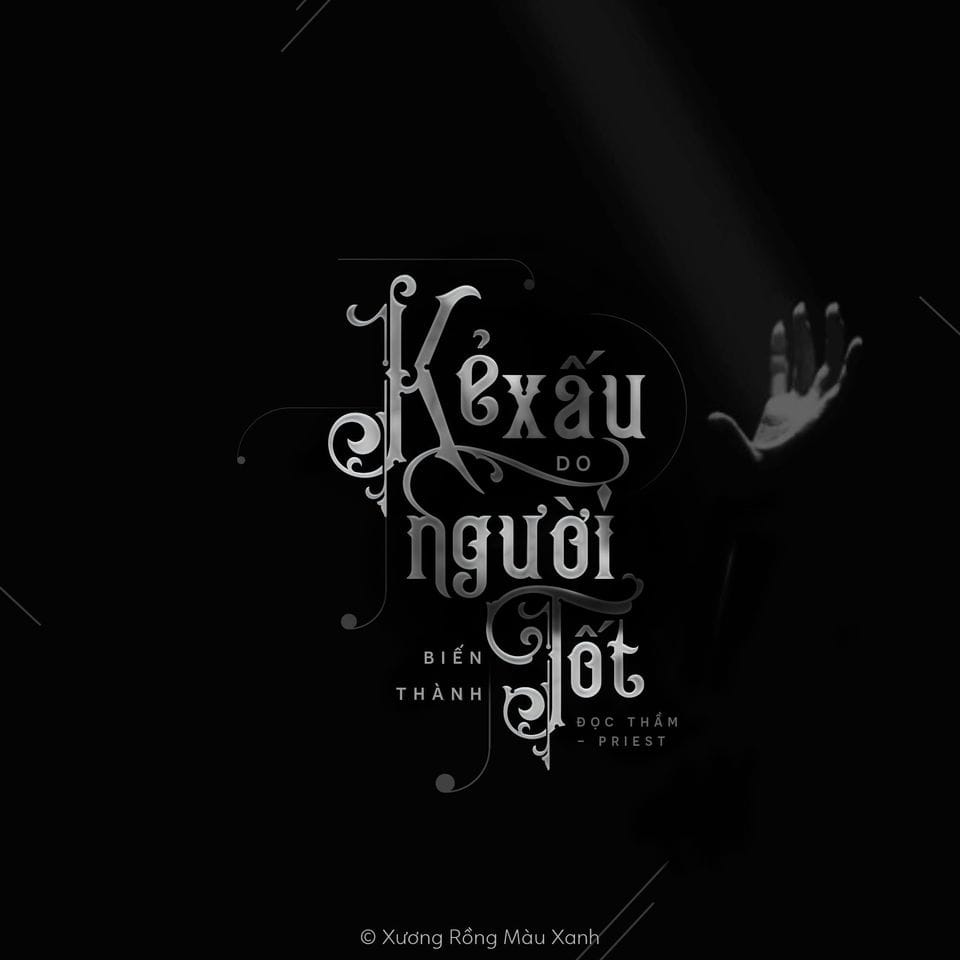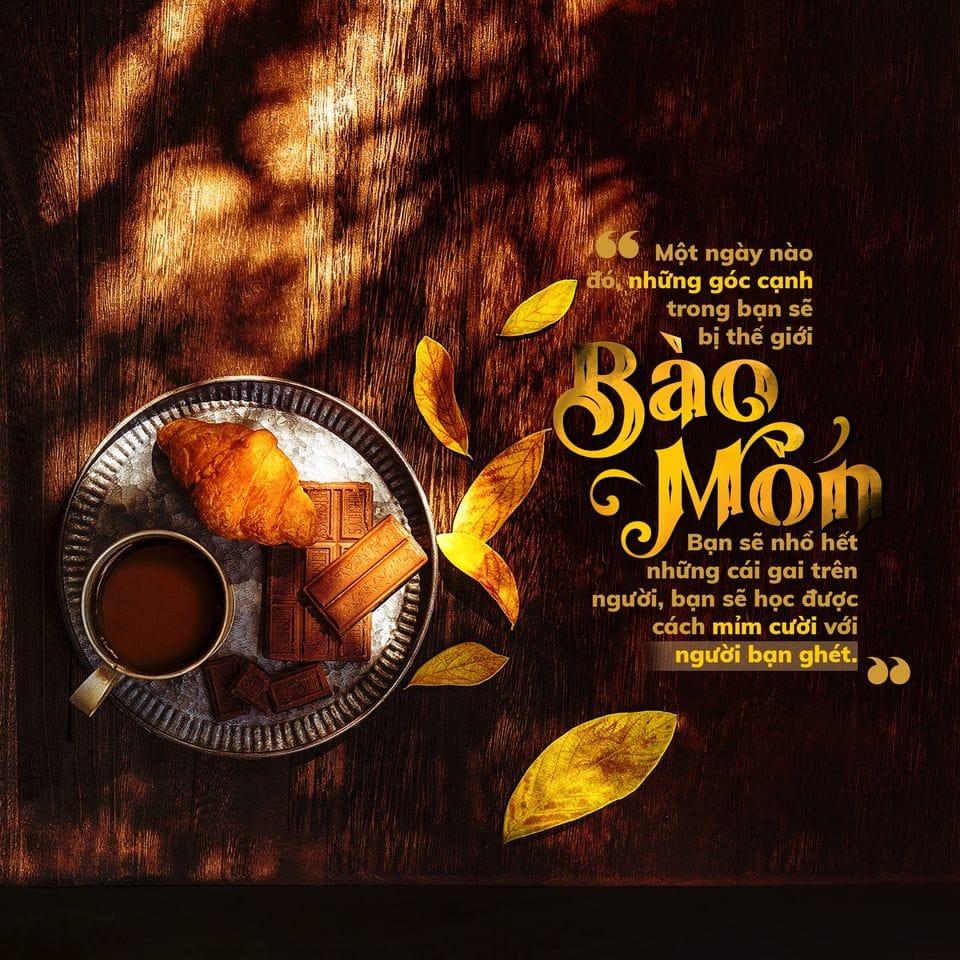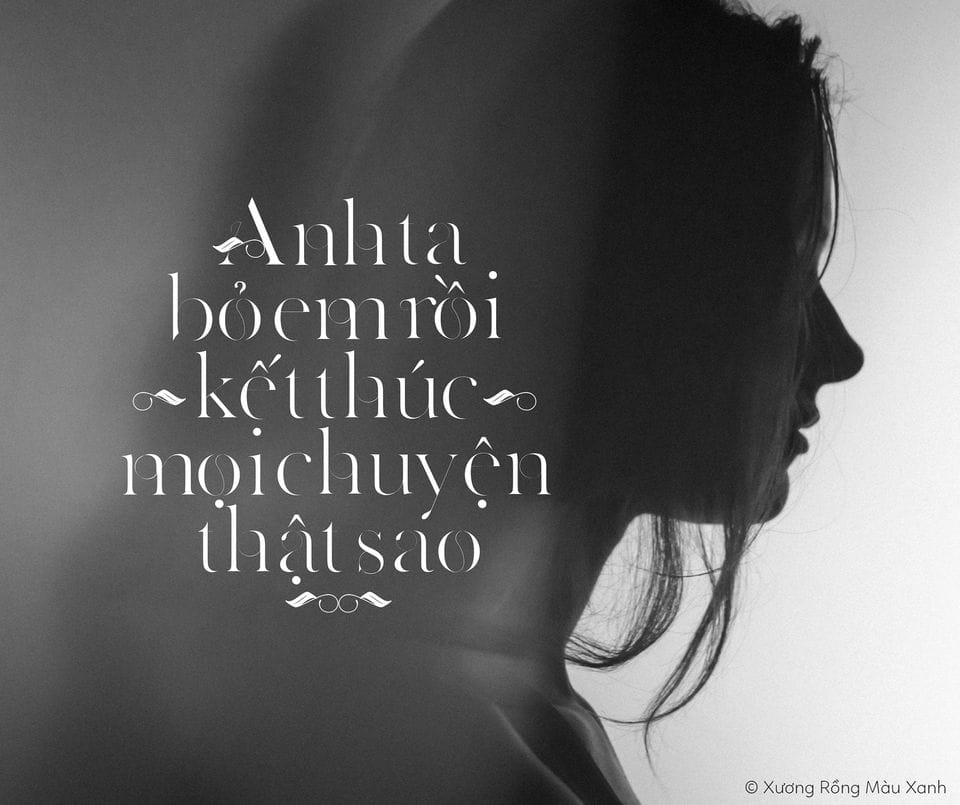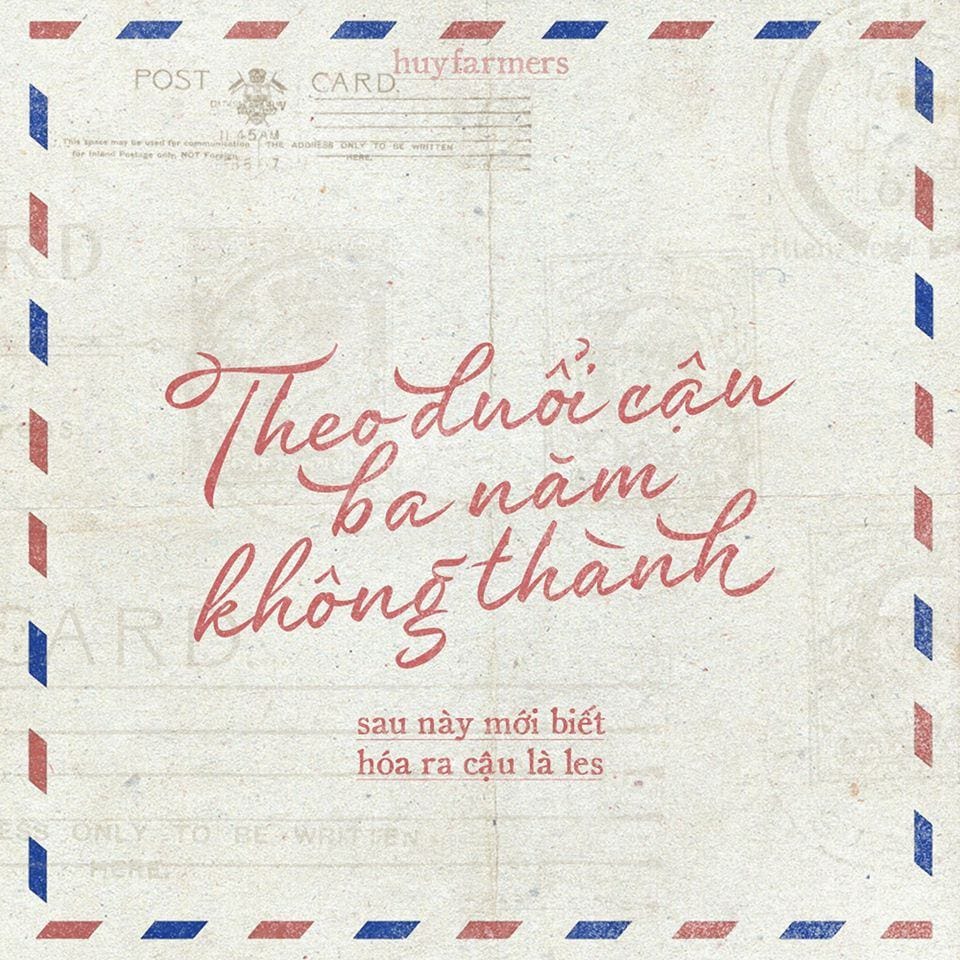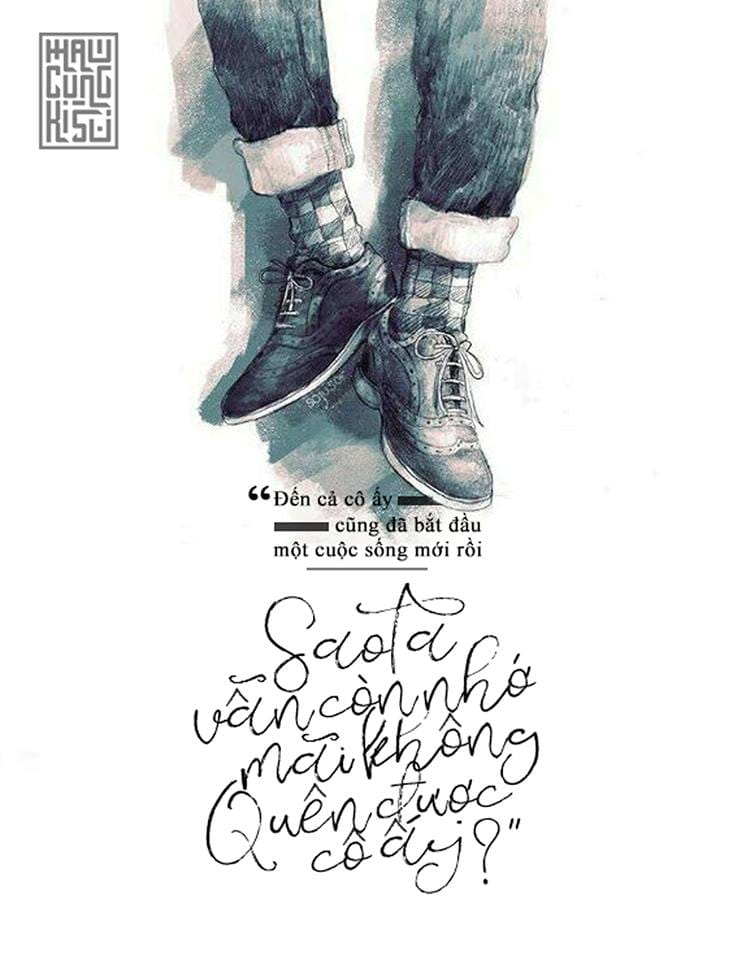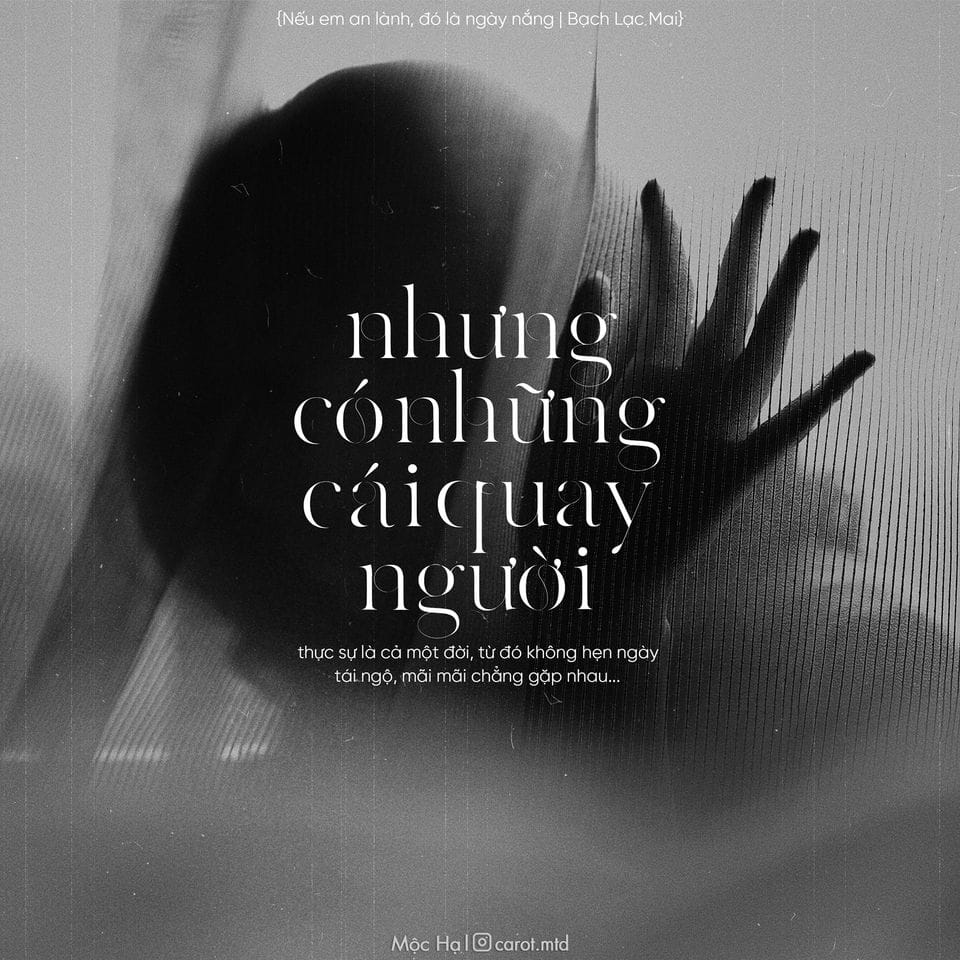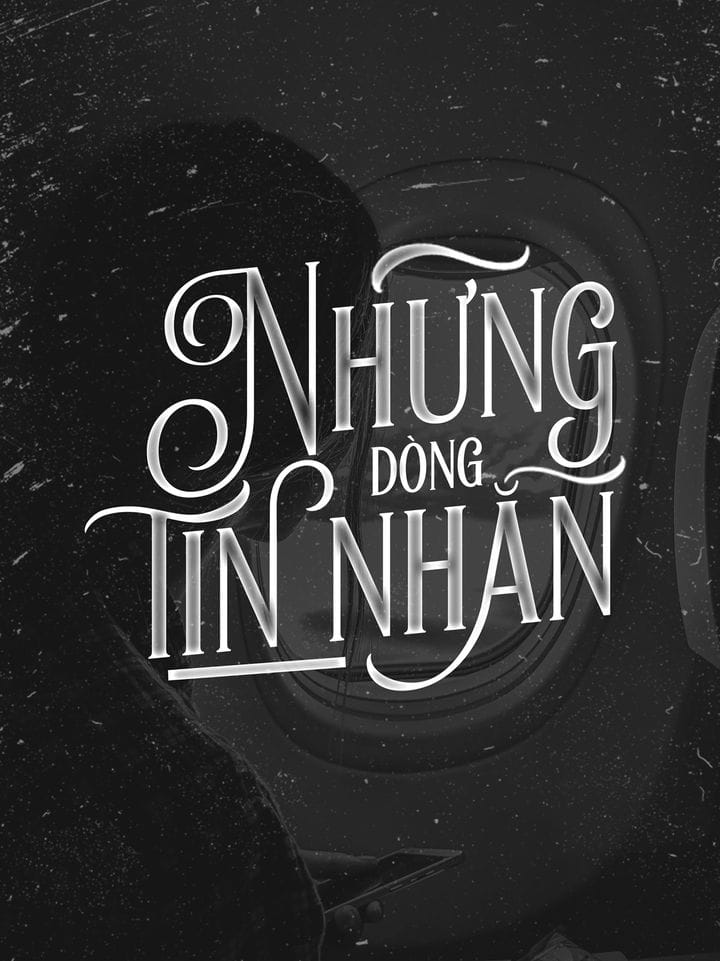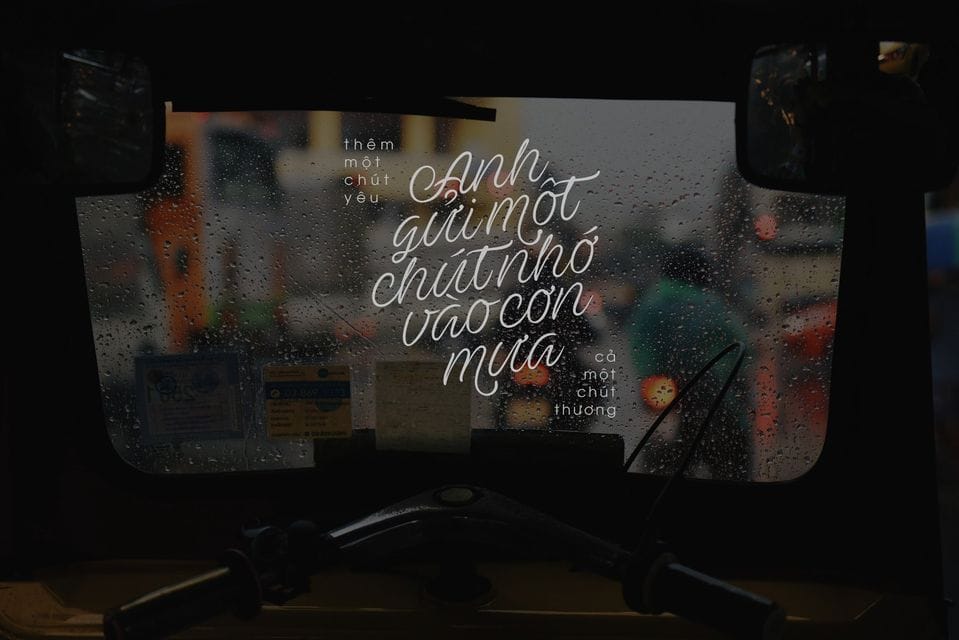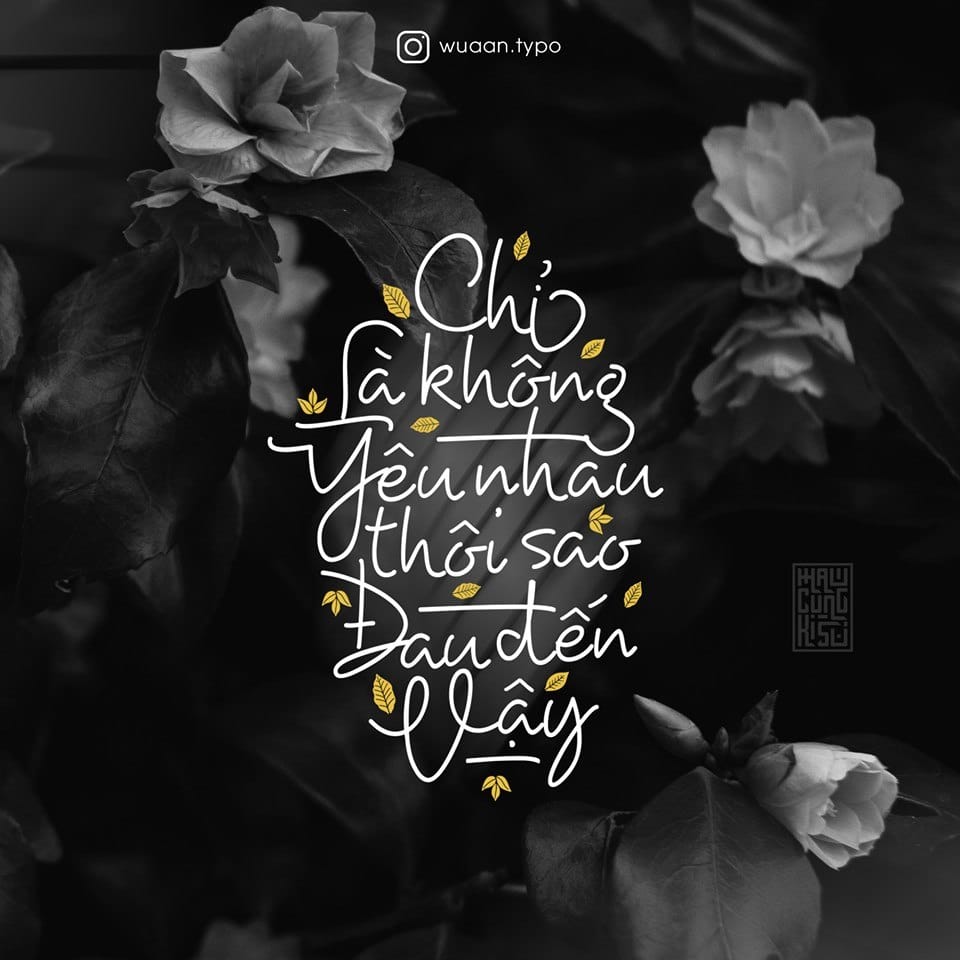
Đây là phần 3 bao gồm 70 font của
bộ font MTD Việt Hóa cực đẹp, có chứa rất nhiều font chữ Script Việt hóa với nhiều phong cách khác nhau rất phù hợp để làm typography cho các video âm nhạc Youtube, banner quảng cáo và nhiều loại hình thiết kế khác.
Việt Hóa bởi Mộc Hạ
Demo một số hình ảnh sử dụng bộ font này:
- MTD 21 Cent
- MTD Antro Vectra
- MTD Arthington
- MTD Artisan
- MTD Ave Utan
- MTD Barakah Regular
- MTD Berrigela Anitta
- MTD Black Baron Gothic
- MTD Blaze Glory
- MTD Britania Letter
- MTD Butter Swany
- MTD Casanova Script EF Pro
- MTD Cindo Kato
- MTD Clarkson Script
- MTD Dartangnon ITC
- MTD Fabulous Script
- MTD Fancy Melody
- MTD Feliz En Vista Alternative
- MTD Feliz en Vista
- MTD Fleurie
- MTD Francesca
- MTD Geraldyne
- MTD Grange
- MTD Hayne Script Clean
- MTD Hipster Script
- MTD Hu Kou
- MTD Hummington
- MTD Jailetter
- MTD Katheryna Swashes
- MTD Katheryna
- MTD LeJardin Floral
- MTD Magnies
- MTD Matsury
- MTD Mirosa Swash
- MTD Mirosa
- MTD Othelie Line
- MTD Othelie
- MTD Palomino
- MTD Rockyeah Brush
- MTD Second Lyrics
- MTD SG Girasol Shine
- MTD SG Girasol
- MTD SpringVibes Floral Light
- MTD SpringVibes Floral
- MTD SpringVibes
- MTD St Friska
- MTD Stash Vintage Light
- MTD Stash Vintage
- MTD Summer Show
- MTD The Moon Falls
- MTD Tita Script Alt
- MTD Verona Lotte
- MTD Palomino DE
- MTD Palomino Sans One
- MTD Palomino Sans Two
- MTD Palomino Script
- MTD Victorian Dingbats Collection
- MTD Queen Victoria
- MTD Queen Victoria Vintage
- MTD Queen Victoria Swash
- MTD Queen Victoria Inline
- MTD Queen Victoria Outline
- MTD Queen Victoria Shadow
- MTD Queen Victoria Inine Swash
- MTD King Edward Shadow
- MTD King Edward
- MTD King Edward Basic Shadow
- MTD King Edward Basic
- MTD King Edward Basic Italic
- MTD King Edward Basic Inline
- MTD King Edward Basic Inline Italic